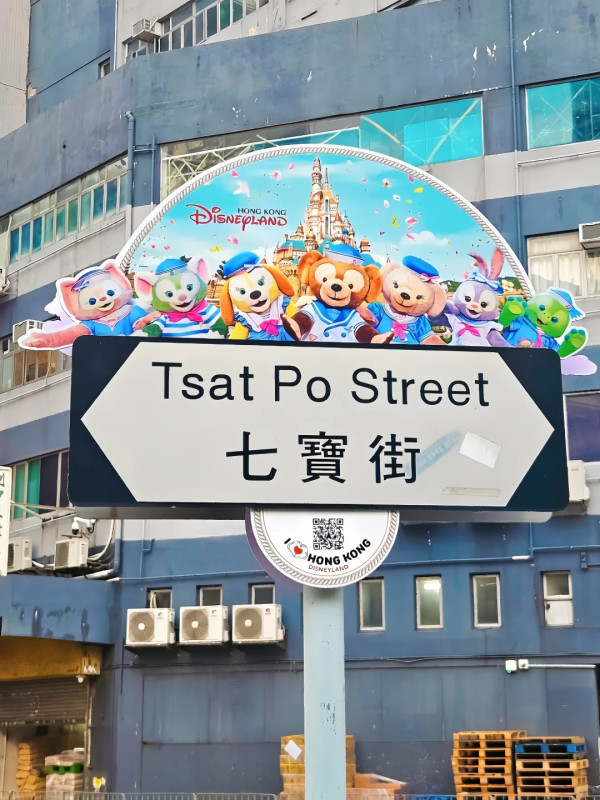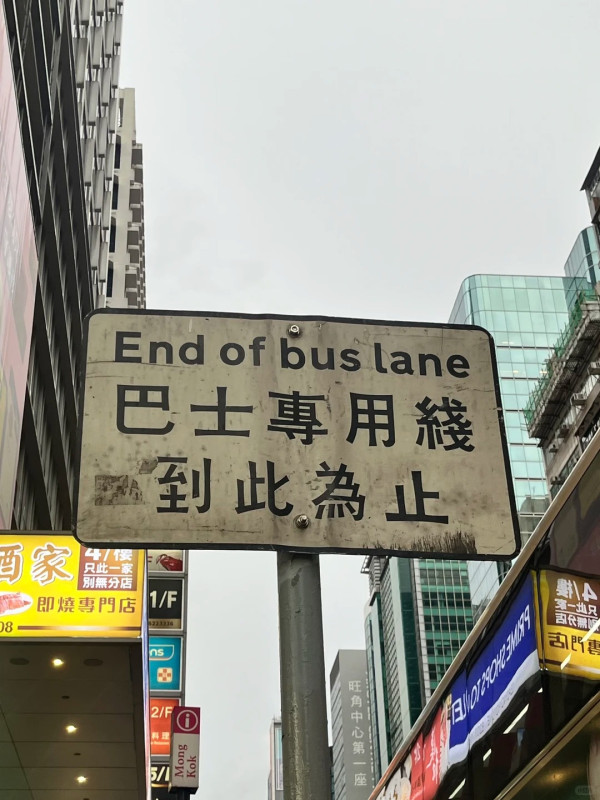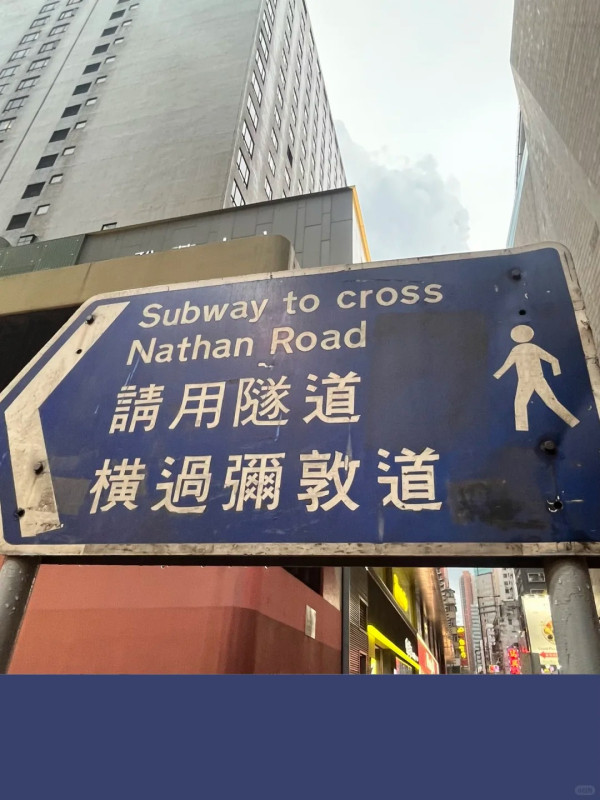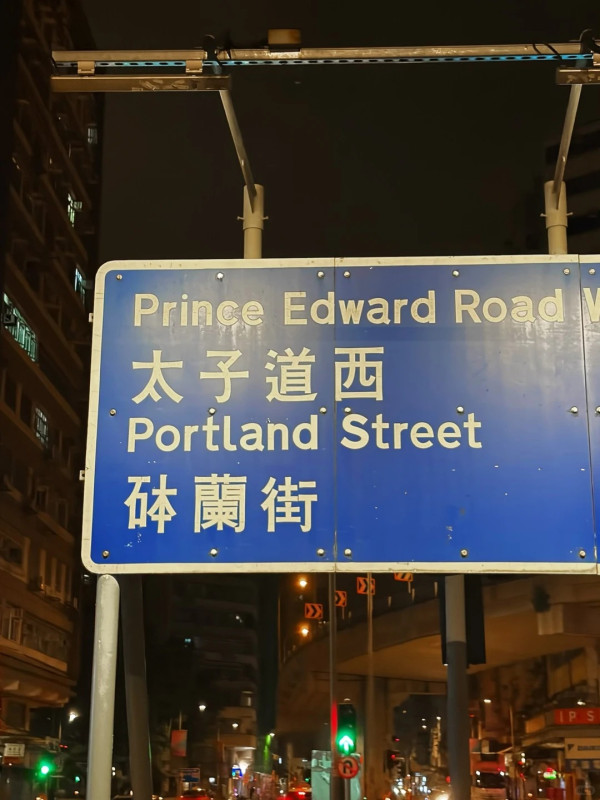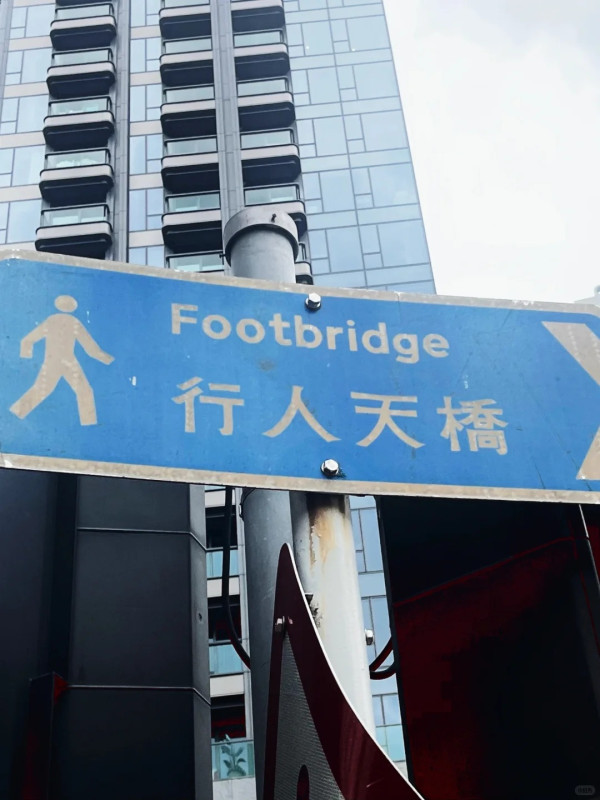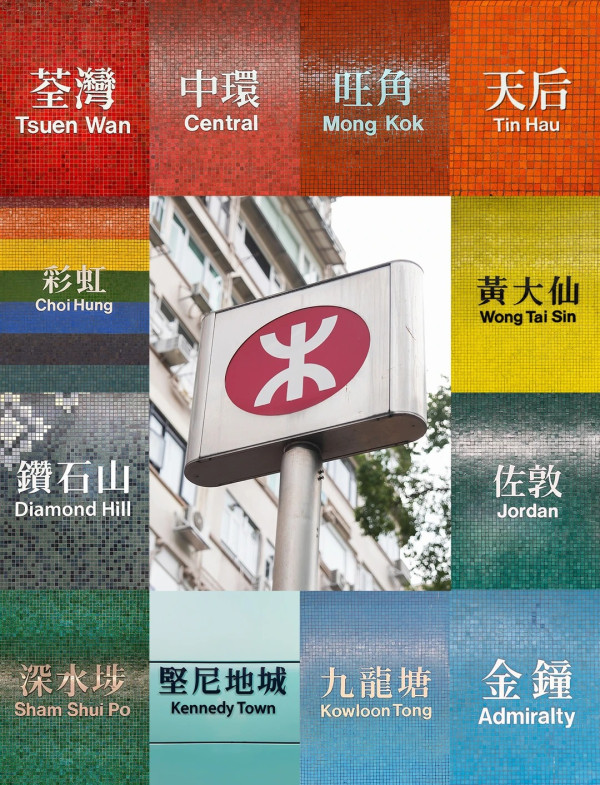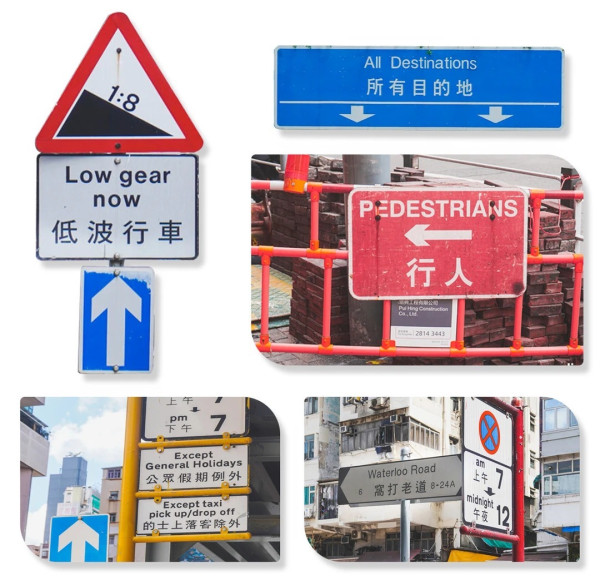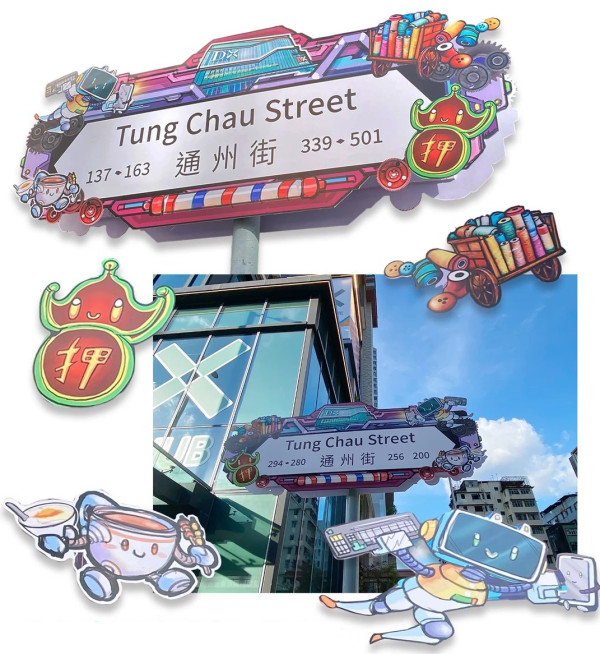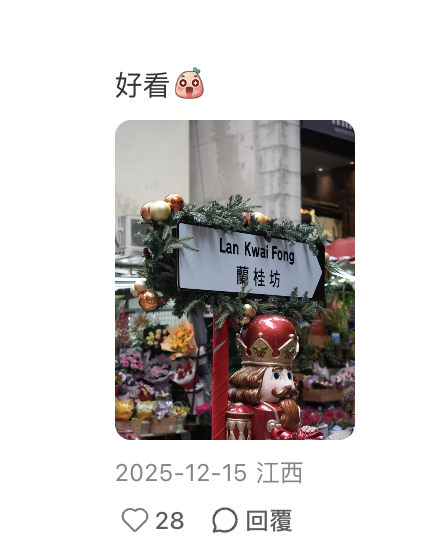
香港路牌設計震驚內地客!網民大讚4大聰明設計:字體配色視覺高級
相信不少人都會發現,許多來港旅客都喜歡拍攝大街小巷的路牌標誌。究竟這些每天陪伴大家出行、看似尋常的公共系統標誌,藏著甚麼視覺魅力與設計秘密?日前,社交平台上有一篇以「香港路牌為什麼都挺好看的」為題的文章,引發數大量網民熱烈討論。不少人紛紛大讚香港路牌視覺質感高級,背後更體現出「以人為本」的4大設計特色!
1. 兼顧美學與辨識度的字體選用
字體是路牌傳遞資訊的核心。香港路牌在英文字型上,主要沿用英國設計師 Jock Kinneir 與 Margaret Calvert 於 1958 年研發的「Transport」字體,利用圓潤的線條與大小寫組合,讓駕駛者在移動中能迅速讀取字樣。
為應對夜間車燈照射產生的光暈現象,路牌設計設有明確規範:深色底白字選用較細的 Transport Medium,淺色底黑字則採用較粗的 Transport Heavy,以維持極高的清晰度。
在中文字體方面,香港亦累積了深厚的在地字型美學。除了常見的「全真中黑體」及早期服刑人士手製的「監獄體」外,第一代港鐵導視系統採用由設計師柯熾堅創作的「地鐵宋」,亦以傳統宋體結構融合圓潤筆觸,展現出獨特的文化風貌。
2. 雙語系統與直觀圖形標示
考慮到香港國際化都市的定位,公共標誌高度貫徹雙語原則,以中英對照配合簡潔的幾何圖形。這種設計邏輯旨在降低閱讀門檻,使不同語言背景的行人與司機都能在短時間內判斷方向與交通規則,體現出以使用者體驗為先的概念。
3. 依據道路情境區分顏色
在色彩應用上,香港路牌主要透過顏色對路段類別進行區隔。快速公路統一使用綠色底色,而一般市區道路則多以藍底白字或白底黑字呈現。這種分層設計不僅便於辨識道路等級,同時也能避免過多高飽和度色彩對街景造成干擾,保持整體視覺的舒適度,不易引發審美疲勞。
4. 融合社區歷史的視覺創新
除了標準化的交通指引,部分地區亦試圖將路牌轉化為在地文化的載體。例如深水埗 DX 設計館周邊的路牌,便嘗試將當地的布料線軸、當鋪招牌及現代科技元素融入指示設計中,為傳統公共設施增添了地域故事與設計活力。
網民大讚:展現獨特街景氛圍與對細節的執著
帖文引起大量網民對公共標示的興趣,不少人表示多了角度去欣賞香港。有網民指出,香港的街頭標誌帶有一種獨特的復古氛圍與城市質感,特別是街道上保留了多種不同時代的字型與歷史痕跡,沒有因千篇一律而顯得死板單調。更有不少旅客表示,視覺美學的執著與本地文化巧妙結合,成為在香港街頭漫步與攝影時不可或缺的特色風景。